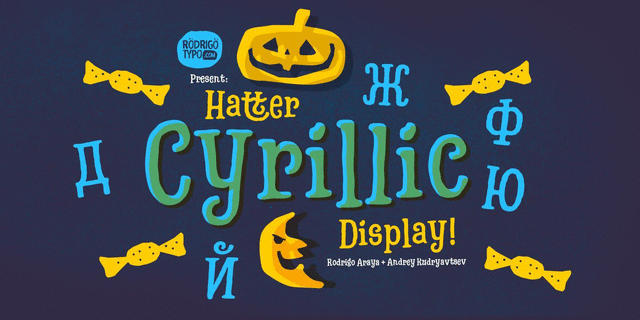
Hatter, шрифт безумного шляпника – это самый хэллоуинский шрифт! Он представляет собой смесь брусковой антиквы девятнадцатого века и леттеринга в стиле фильмов Тима Бертона: Алиса в Стране Чудес, Труп Невесты, Кошмар перед Рождеством и других. Шрифт одновременно напоминает жуткого Франкенштейна и молодую ведьму.
Hatter содержит латиницу и кириллицу, поэтому им можно пугать людей почти по всему миру =)
Шрифт призвали к жизни Родриго Арая Салас и Андрей Кудрявцев в полнолуние пятницы 13-го 2017 года.